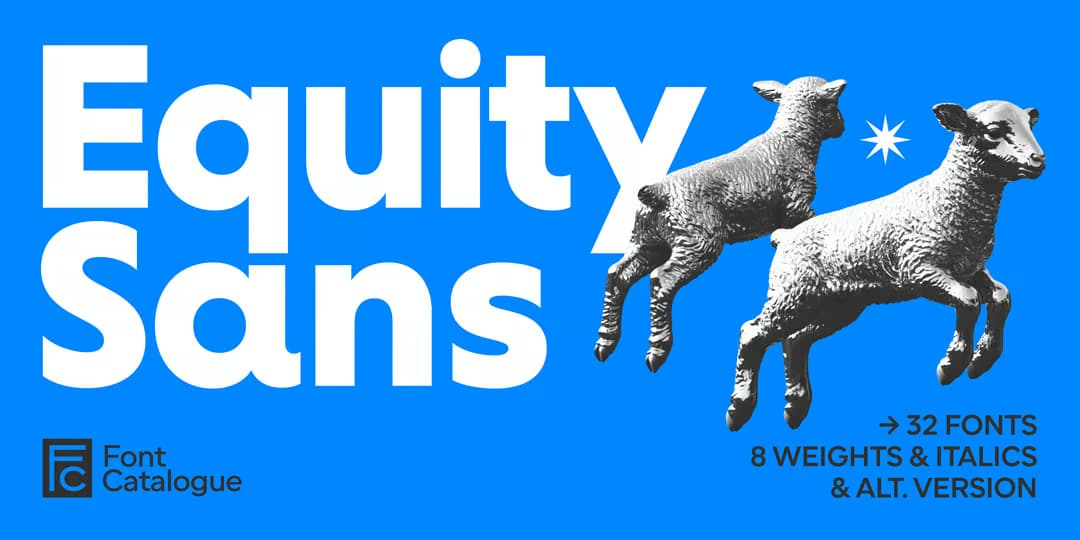
Equity Sans
やっぱり作られ続けるジオメトリックサンセリフの新作。ほんのりヒューマニスト風味が加味されており、ちょこちょこ幾何学を崩して「字」としての形が調整されている。g は普通の1階建ての他に2種類のオルタネートがあり、2階建てのループが開いたものと、開きの向きが逆になっているのがおもしろい。M は両足が傾いてるのと垂直のものがある。他は丸数字と、顔文字があるのが珍しいだろうか。イタリックもあって8ウェイト。